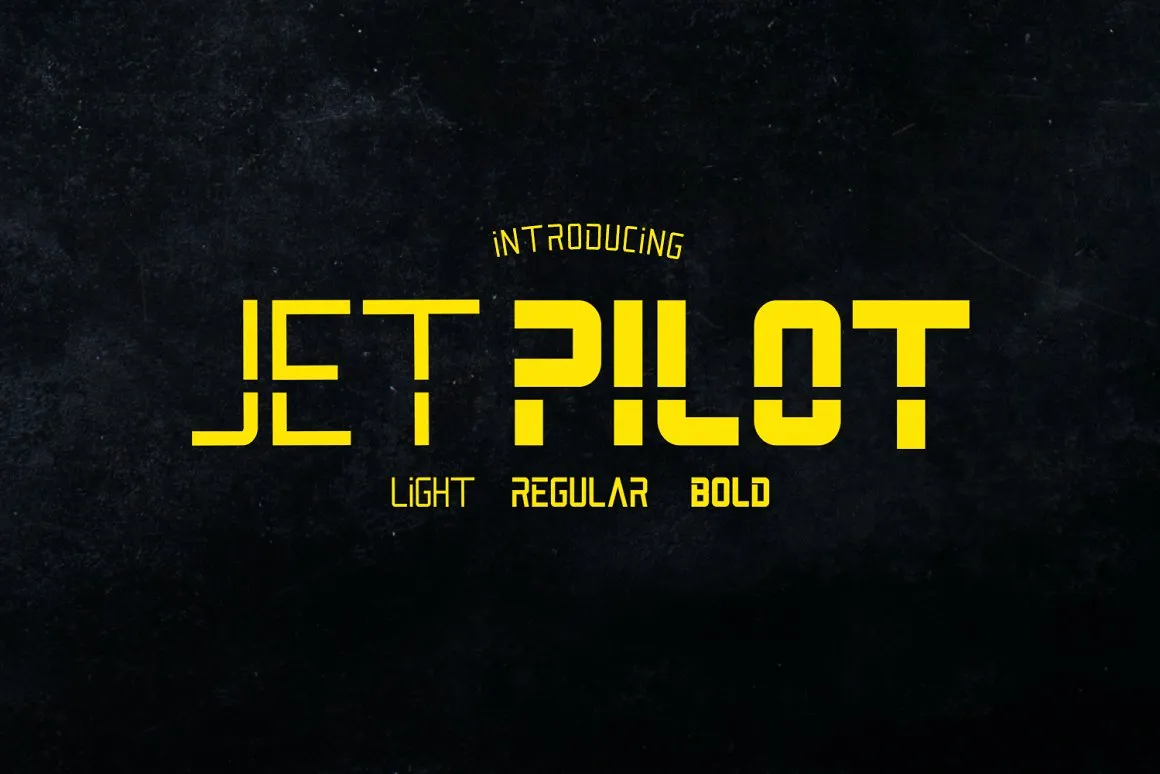
Jet Pilot Font – Fonte Grátis
Jet Pilot Font
Aproveite esse novo lançamento que eu estou preparado para compartilhar com vocês hoje – a Jet Pilot Font! Ela é uma moderna tipografia minimalista, perfeita para quem procura um design limpo e sofisticado. O Jet Pilot vem em três opções de tamanho: Light, Regular e Bold, tornando-o extremamente versátil para qualquer projeto que você possa estar desenvolvendo. Com seus caracteres em maiúsculas sólidos, a Jet Pilot é perfeita para criações gráficas modernas. Esta fonte apresenta um estilo minimalista claramente visível e oferece uma variedade de opções para adaptá-la ao seu projeto específico. Seja para criações digitais ou impressões, o Jet Pilot se destaca como uma escolha intuitiva e funcional. O design simples mas elegante da Jet Pilot torna-a perfeita para qualquer aplicação onde você precise de um estilo moderno e minimalista em sua próxima peça de trabalho gráfica.